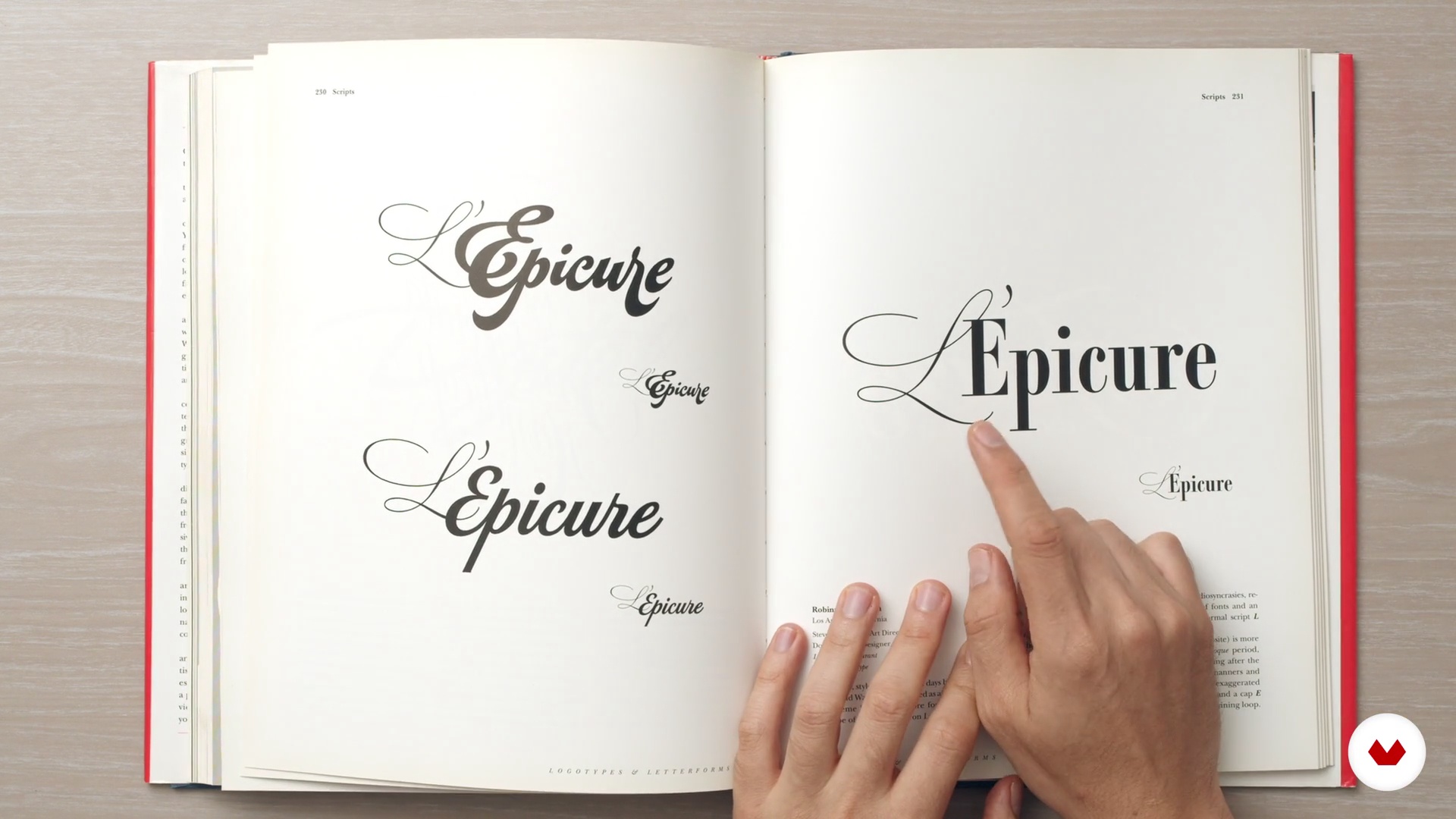
Dostosowanie krojów pisma do projektu logotypów
Wprowadzenie do typografii i brandingu
“W tej lekcji zobaczymy krótkie wprowadzenie do typografii, jej historycznej ewolucji oraz jej relacji z marką (tożsamość korporacyjna) jako czynnika zwiększającego sprzedaż. ”
Na tej lekcji wideo Monotypo Studio porusza temat: Wprowadzenie do typografii i brandingu, która stanowi część kursu na platformie Domestika: Dostosowanie krojów pisma do projektu logotypów. Poznaj proces modyfikacji czcionki i kształtowania unikalnej tożsamości marki.
“Teraz. gdy omówiliśmy trochę więcej o mojej karierze. o mojej pracy. przejdziemy do... Bezpośredniej rozmowy o typografii i jej związku z marką ponieważ jest to kluczowe dla możliwości zacząć realizować wszystkie plany na kursie. Najpierw pokażę wam postęp historii marki... W tej lekcji. Lubię umiejscawiać ją od czasów grecko-rzymskich. szczególnie z kolumną Trajana. Były to pierwsze litery. które zostały narysowane w alfabecie zachodnim w sposób bardzo wyraźny. Tutaj możemy zobaczyć reinterpretację. która została wykonana z nich w epoce przez... artystę i rytownika Albrechta Dürera. Możemy...”